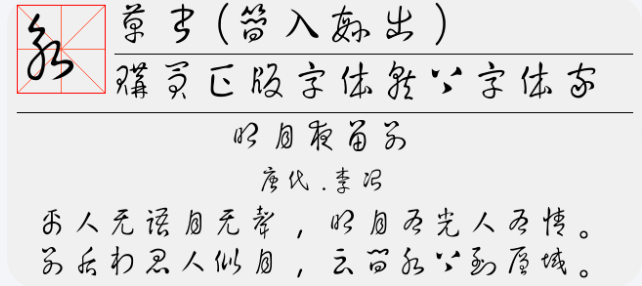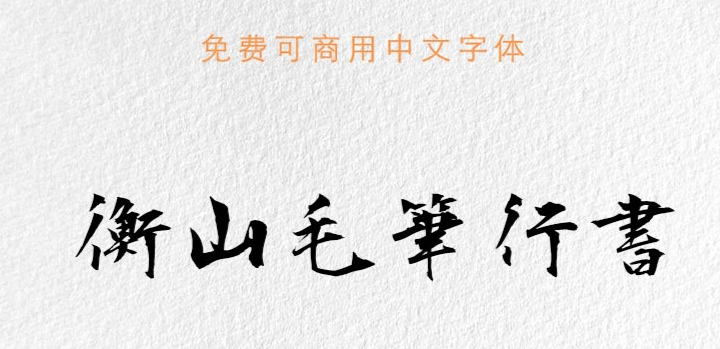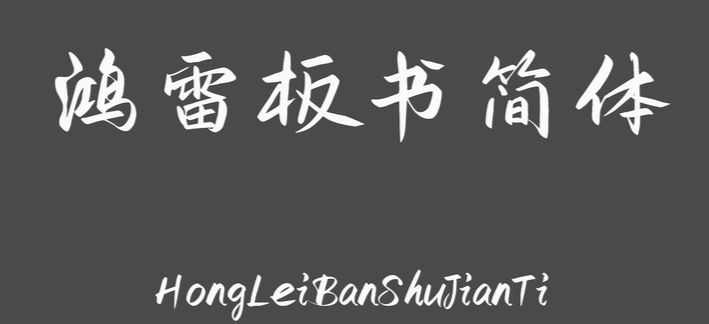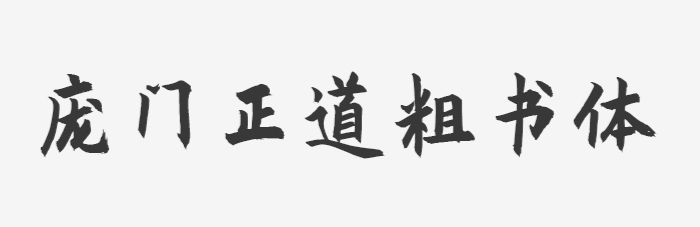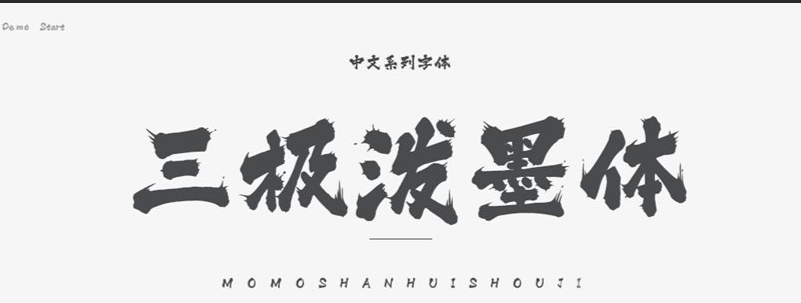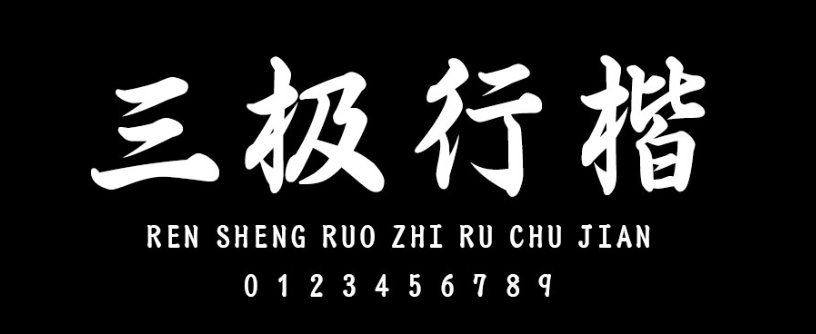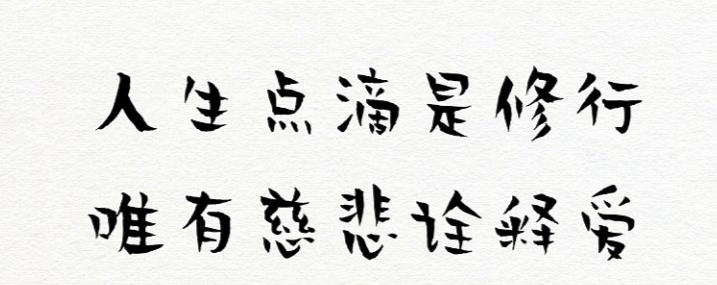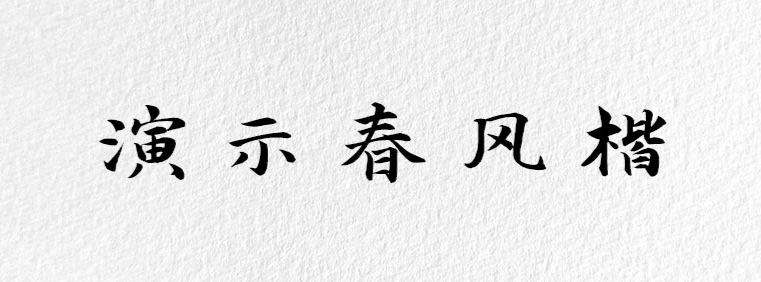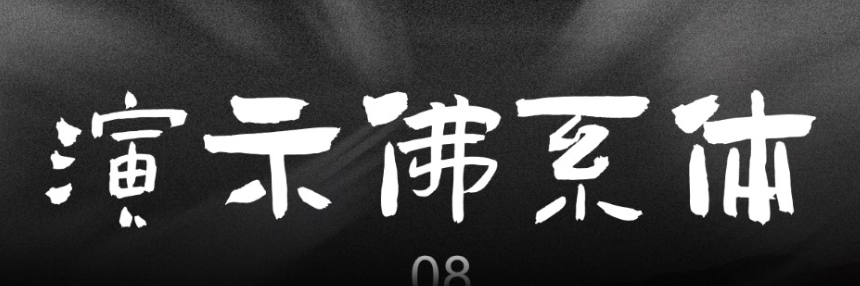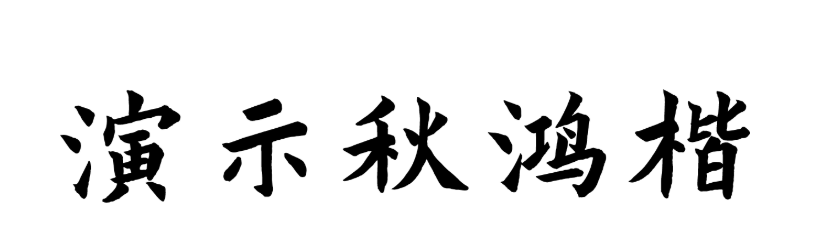
本文分享精选的17款书法艺术免费可商用字体,它们不仅展现了书法的韵味,也符合现代审美需求,适合设计师和企业在各种项目中使用。
1;草书(简入繁出):这款字体以草书为基础,将简体字转化为繁体字,展现了草书的流畅与变化。
2;衡山毛笔行书:衡山毛笔行书以其自然流畅的笔触,呈现出行书的灵动之美。
3;鸿雷板书简体:这款字体以板书风格为基础,简体字的设计使其更加适合现代应用。
4;马善政毛:这款字体以其独特的笔触和结构,展现了毛笔书法的力度与个性。
5;莫大毛笔体:莫大毛笔体以其雄浑的笔触和大气的结构,适合用于标题和标识设计。
6;庞门正道粗书体:这款字体以其粗犷的笔触和正道的字形,适合用于强调力量和决心的场合。
7;千图笔锋手写体:千图笔锋手写体以其手写风格,展现了书法的自然和亲切感。
8;三极泼墨体:这款字体以泼墨技法为基础,展现了书法的自由和创意。
9;三极行楷简体:三极行楷简体以其行楷风格,适合用于需要兼具美感和易读性的场合。
10;贤二体:贤二体以其简洁的笔触和结构,适合用于简约风格的设计。
11;演示春风楷:这款字体以其春风般的温暖和柔和,适合用于温馨和亲切的场合。
12;演示佛系体:演示佛系体以其平和的笔触和结构,适合用于传达宁静和禅意的设计。
13;演示秋鸿楷:这款字体以其秋鸿般的高远和深邃,适合用于表现秋天的氛围和意境。
14;演示夏行措:演示夏行措以其夏日的活力和热情,适合用于表现夏日的热烈和生机。
15;演示悠然小楷:这款字体以其悠然的笔触和结构,适合用于表现轻松和自在的氛围。
16;钟齐流江毛草:钟齐流江毛草以其流江般的流畅和自然,适合用于表现书法的灵动和变化。
17;钟齐志葬行书:这款字体以其志葬行书的风格,适合用于表现书法的庄重和肃穆。